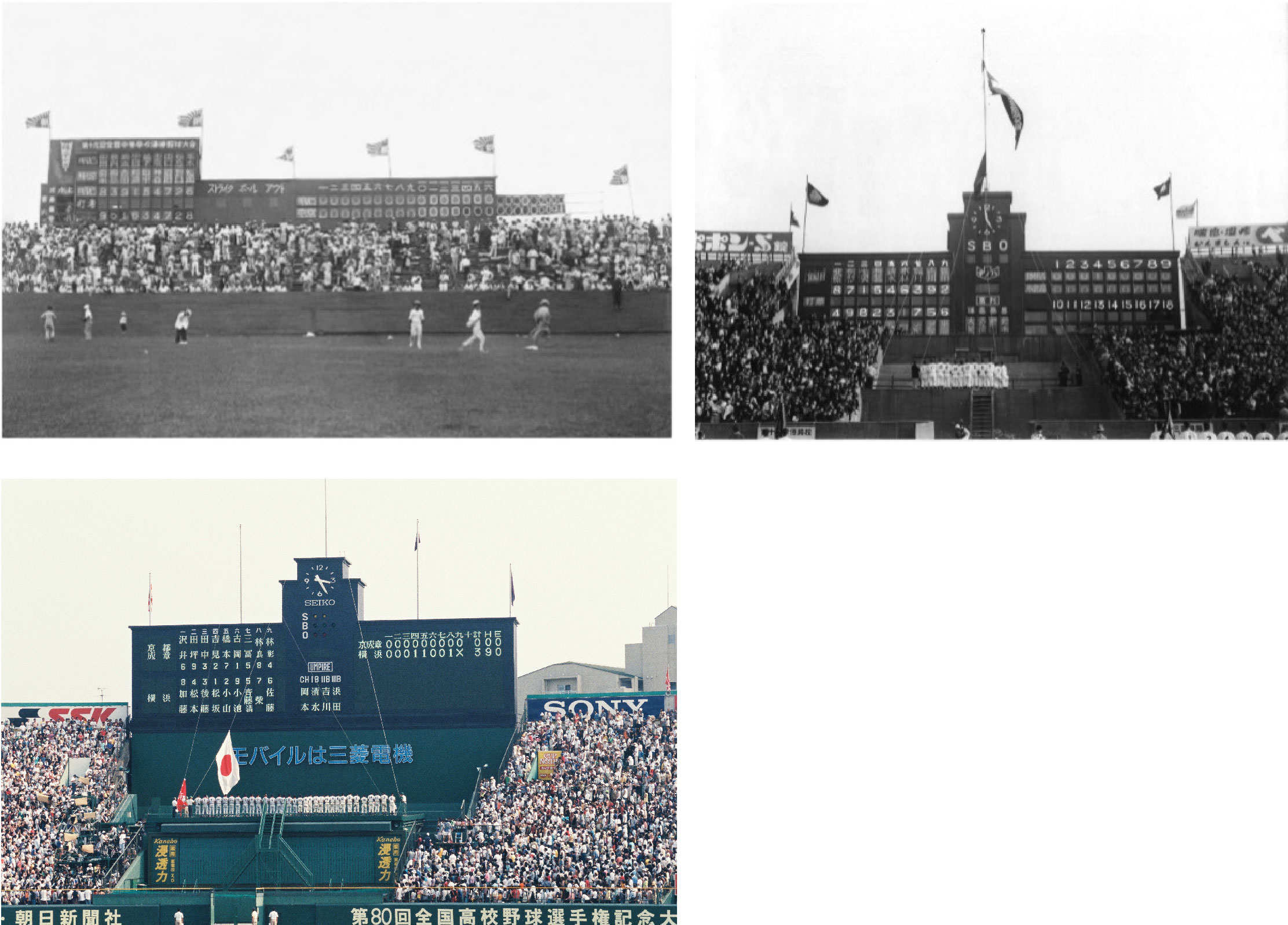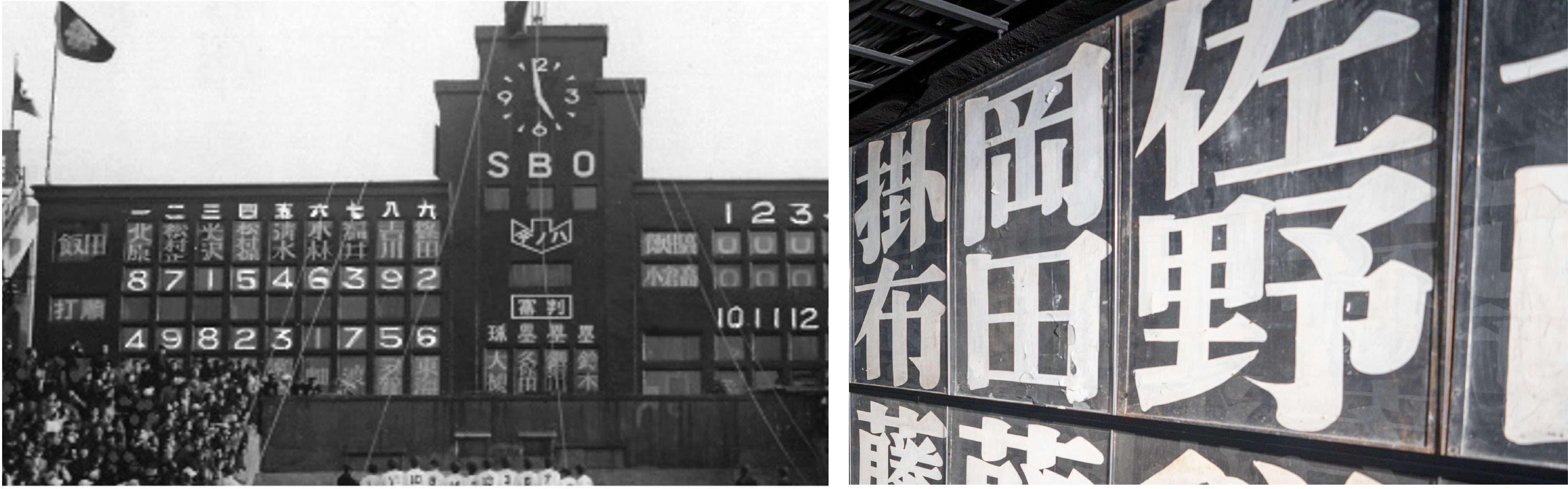
モリサワ 阪神甲子園球場と100周年記念共同プロジェクト 伝統の「甲子園文字」を受け継ぐ『甲子園フォント』制作が決定!
株式会社モリサワ(代表取締役社長:森澤彰彦 本社:大阪市浪速区敷津東2-6-25 Tel:06-6649-2151 代表、以下モリサワ)は、2024年7月24日に、創業者森澤信夫らが「邦文写真植字機」を発明して100周年を迎えます。同じく、阪神電気鉄道株式会社(代表取締役社長:久須 勇介 本社:大阪市福島区)が運営する阪神甲子園球場も、同年8月1日に開場100周年を迎えます。これを記念して、阪神甲子園球場とモリサワは、100周年記念共同プロジェクトとして、同球場のスコアボードで使用してきた伝統の「甲子園文字」を受け継ぎ、『甲子園フォント』として制作、デジタルフォント化することを決定しました。
阪神甲子園球場のスコアボードでは、1983年まで、職人が黒い板に毛筆で手書きをした文字を使用しており、その独特な字形が「甲子園文字」として親しまれ、スコアボードを電光掲示に改修した1984年以降も、その伝統を受け継ぐべく、同球場の職員がオリジナルの文字データを制作し表示してきました。本プロジェクトは、文字のプロフェッショナルとして歴史を紡いできたモリサワが、阪神甲子園球場が大切に受け継いできた「甲子園文字」を、現代の実用に即した『甲子園フォント』として制作するものです。「甲子園文字」の伝統を次の時代に繋ぐコンセプトで、より多くの方の読みやすさに配慮したUD(ユニバーサルデザイン)フォントをベースとしています。『甲子園フォント』の完成は2024年12月頃を予定しており、2025年シーズンから、阪神甲子園球場のスコアボードで使用される予定です。
(右)手書き時代の選手名板
『甲子園フォント』制作プロジェクトの概要
企 画:阪神電気鉄道株式会社、株式会社モリサワ
内 容:阪神甲子園球場のスコアボードに表示されてきた「甲子園文字」を、株式会社モリサワによりデジタルフォント化するプロジェクト
完成時期:2024年12月(予定)
使用開始:2025年3月(予定)
阪神甲子園球場のスコアボード・表示される文字の歴史
甲子園球場が開場した翌年1925年に初代スコアボードが誕生しました。木製で、表記できる最大のイニングスコアは延長16回まででした。
1934年には2代目スコアボードに代わり、木製からコンクリート製となり、戦火を乗り越え、約半世紀にわたって使用されました。さらに1984年以降は3代目スコアボードに代わり、文字表示が手書きの黒板から電光掲示方式へと変更されました。黒地のボードに白色ブラウン管を採用することで、先代のスコアボードの姿を継承し、選手名・チーム名表記には、手書き時代を踏襲した字体が使用されました。
1984年に選手名や得点スコアの表記が電光化されるまで、スコアボードの中には文字書きを行う職人たちが従事していました。長年、スコアボードから映し出されてきた人間味のある文字は、甲子園球場特有の味わいを演出し、手書きから電光式に姿を変えた今も継承されています。
(右上)2代目スコアボード / 提供:阪神電気鉄道株式会社
(左下)電光化されたスコアボード / 提供:朝日新聞社